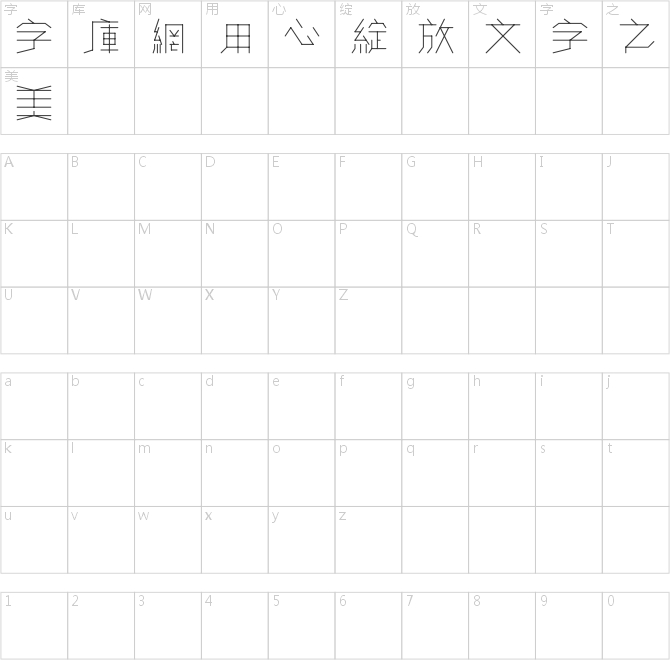
字体名称: 黄令东细线体
黄令东细线体
黄令东细线体介绍
黄令东细线体是一款十分特别的字体,这款字体是用程序自动生成,用递归根式包装语言(RRPL)进行编写。在RRPL中,每个汉字被描述为数字、符号和对其他字符的引用的短字符串。它的语法灵感来自标记语言,如乳胶,以及传统的用于书法练习的“米”网格。
目前黄令东细线体使用5000+的繁体汉字和词根,其字形由默认解析器生成。如有兴趣,可以点击这里去观看字体生成的演示程序。由于是程序自动生成的字体,所以难免会有错别字,大家使用时请检查清楚。
值得注意的是,这款字体是繁体的词根,输入简体字的话会直接映射成繁体字形。比如说你输入“汉”字,会被成繁体的“漢”字。